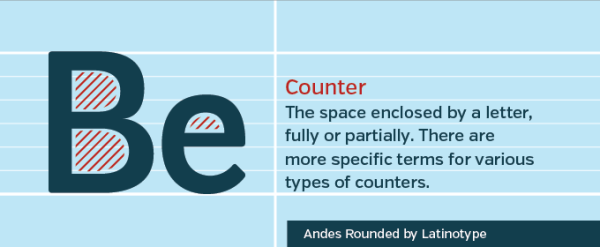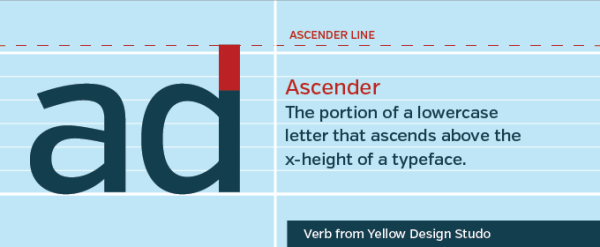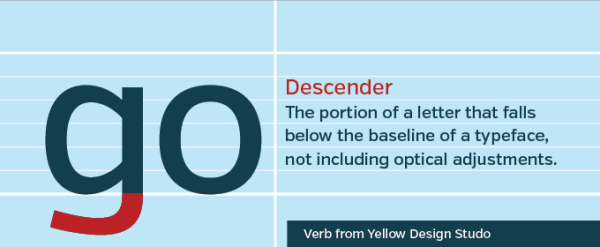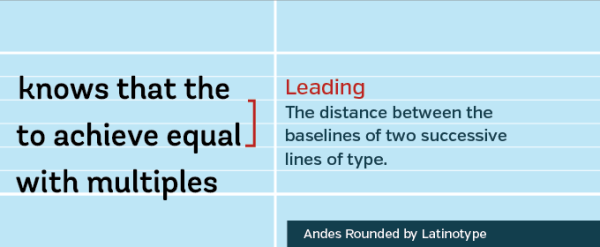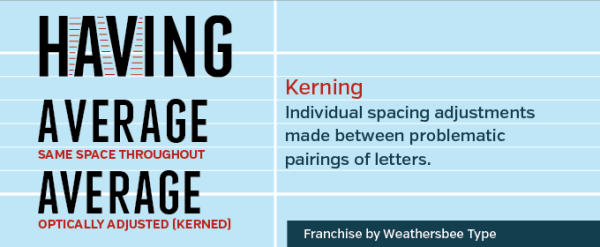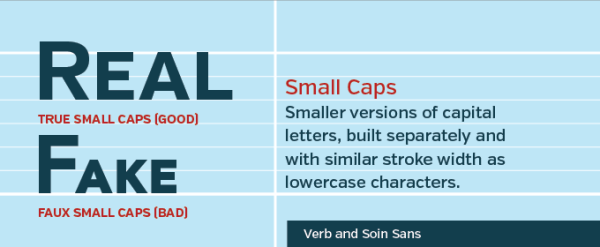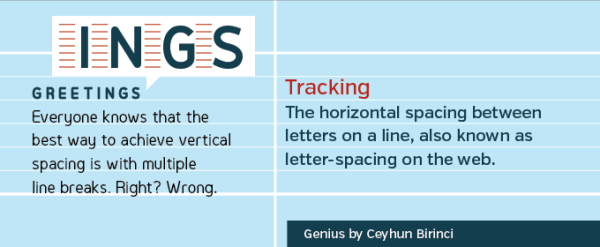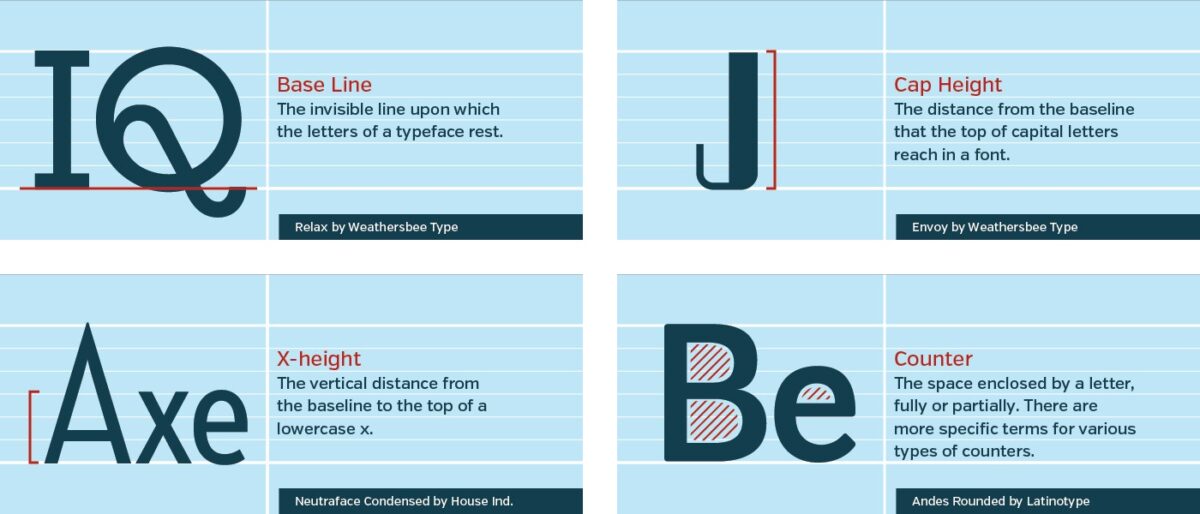
Typographie : 10 définitions à connaître
Les pros du numérique ont parfois un langage… particulier. Quand le community manager regrette « la baisse du reach de ses posts organiques », le graphiste t’explique que ta créa ne convient pas car « les descendantes de la première ligne chevauchent les jambages supérieurs de la seconde ». Creative Market l’a bien compris et publie un petit lexique illustré de la typographie, en 10 définitions.
Ligne de base (baseline)
La ligne invisible sur laquelle reposent les lettres. Certaines lettres (telles que g, j, p, q, y…) peuvent dépasser, selon la police de caractères utilisée.
Hauteur de capitale (cap height)
La distance (verticale) entre la ligne de base et le haut d’une lettre en majuscule.
Œil, hauteur d’X (X-height)
La distance (verticale) entre la ligne de base et le haut d’une lettre minuscule (hors ascendante).
Contrepoinçon (counter)
L’espace « emprisonné » totalement ou partiellement au sein d’une lettre.
Ascendante (ascender)
La partie supérieure d’une lettre qui dépasse de l’œil (au-dessus). On parle aussi de jambage supérieur.
Descendante (descender)
La partie inférieure d’une lettre qui dépasse de l’œil (en dessous). On parle aussi de jambage inférieur.
Interligne (leading)
Distance (verticale) qui sépare les lignes de base de deux lignes de texte consécutives.
Approche (tracking)
Espacement (global) entre les lettres d’une même ligne (sur le web : letter-spacing).
Crénage (kerning)
Ajustement de l’espacement (individuel) de paires de lettres particulières afin d’harmoniser l’écriture.
Petites majuscules (small caps)
Version réduite des majuscules, généralement de même taille que les minuscules. On distingue les véritables petites majuscules, conçues par le designer et intégrées à la typographie ; et les fausses petites majuscules, générées automatiquement par les programmes et pas toujours très homogènes.